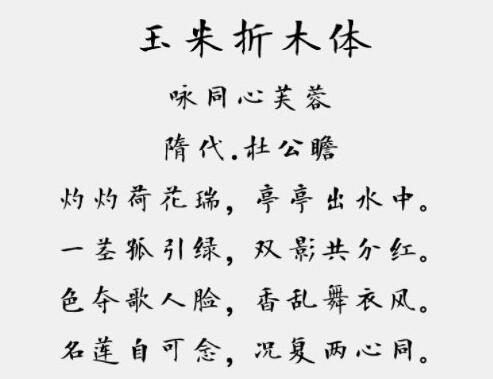
玉米折木體字體是一款古風十足的中文字體,該字體字跡墨采飛動、風度超逸,擁有非常流暢的字體筆畫,排版也非常獨特,仿若樹枝版筆直中正,又或如波浪一般,有高有低,一定會給你帶來意想不到的效果,可以很好的應用于文本裝潢、信息展示、網頁設計、篆刻制模、數據制作、裝潢設計、計算藝術設計、視覺設計、字帖等一切合法應用場景,有喜歡的朋友可免費下載收藏。